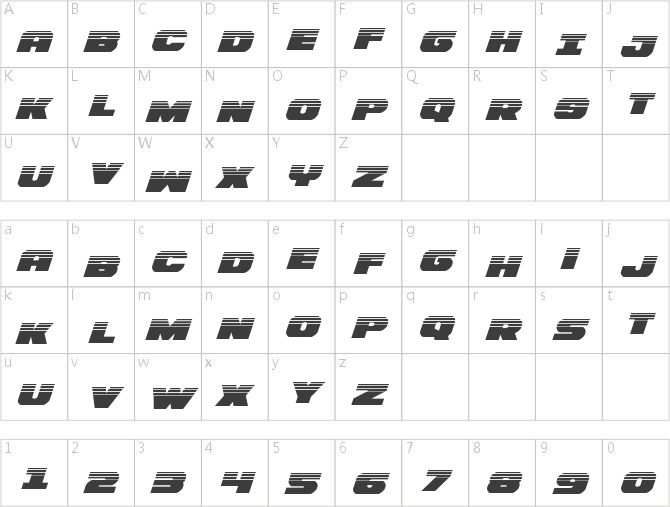
bummerhalfital
bummerhalfital介紹
bummerhalfital字體字庫是一款讓人賞心悅目、百看不厭的英文字體,適合各類廣告和產(chǎn)品包裝設(shè)計(jì)應(yīng)用,字體大小0.04MB,格式為ttf字體,上傳用戶是翰池書法,作者/版權(quán)方為未知